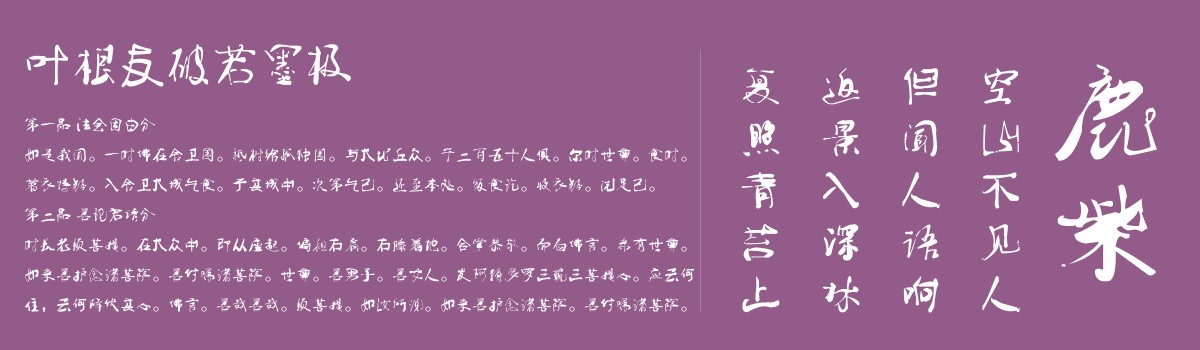
叶根友破若墨极
字体作者:叶根友
创作年代:2016年
字体字数:6763个中文汉字以及其他英文字母和阿拉伯数字
字体介绍
叶根友破若墨极是一款特殊的字体,不是传统的毛笔书写,是用IPAD和手指写成的,感谢高科技带给我们的书法体验,这样的创作很美妙,相信以后还会出来更多这样科技与书法结合的字体作品,这套叶根友破若墨极的字体的笔画与传统的毛笔创作的笔锋是完全不一样的,包含圆角,点、横等都有令人意想不到的效果。